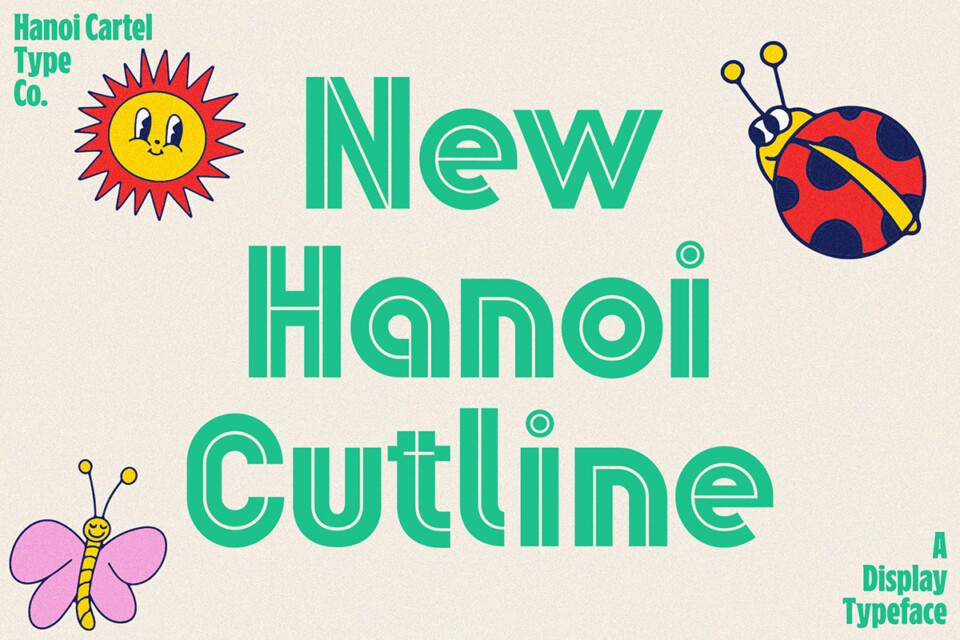
Giới thiệu về Font tiếng Việt New Hanoi Cutline
Trong thế giới thiết kế đồ họa hiện đại, việc tìm kiếm một bộ Font Miễn Phí mang đậm bản sắc văn hóa dân tộc luôn là ưu tiên hàng đầu của các bạn học sinh và giáo viên. Font tiếng Việt New Hanoi Cutline là một tác phẩm typography độc đáo, được lấy cảm hứng từ những nét chữ kẻ biển hiệu xưa cũ tại Hà Nội. Với những đường cắt tinh tế (cutline), bộ font này không chỉ mang lại cảm giác hoài cổ mà còn thể hiện sự phá cách, hiện đại trong từng nét chữ. Đây là lựa chọn hoàn hảo cho các dự án thiết kế slide bài giảng, làm báo tường hoặc tạo các ấn phẩm truyền thông mang phong cách retro cho nhà trường. Việc sử dụng font chữ này giúp tôn vinh vẻ đẹp của chữ quốc ngữ một cách đầy nghệ thuật và sáng tạo.
Ưu điểm nổi bật của Font tiếng Việt New Hanoi Cutline
Thiết kế độc đáo và tính ứng dụng cao
Font tiếng Việt New Hanoi Cutline sở hữu cấu trúc hình học mạnh mẽ kết hợp cùng các khoảng hở đầy ý đồ giữa các nét chữ. Điều này tạo nên hiệu ứng thị giác mạnh mẽ, giúp tiêu đề bài viết trở nên nổi bật hơn bao giờ hết. Đối với các bạn học sinh, bộ font này rất phù hợp để làm bìa tiểu luận hoặc trang trí video clip kỷ niệm lớp.
Tối ưu hóa tiếng Việt hoàn chỉnh
Khác với nhiều bộ font quốc tế, phiên bản này đã được việt hóa chỉn chu, đảm bảo các dấu thanh như huyền, sắc, hỏi, ngã, nặng được đặt đúng vị trí, không bị lỗi hiển thị. Điều này giúp văn bản luôn chuyên nghiệp và dễ đọc trên mọi thiết bị điện tử.
Kết luận và tải xuống